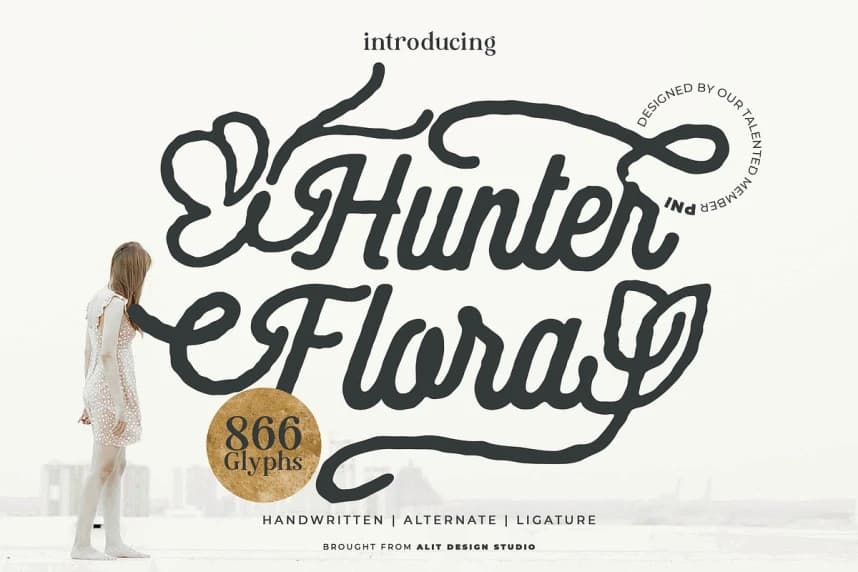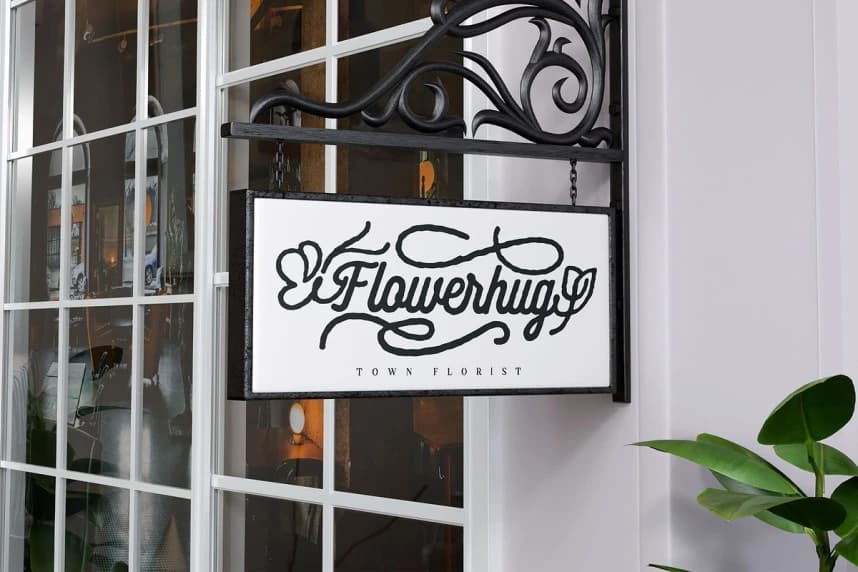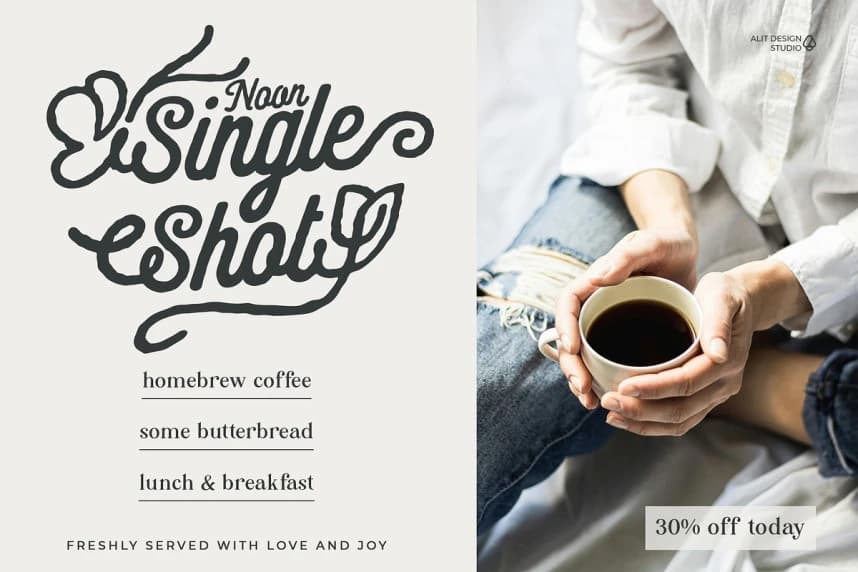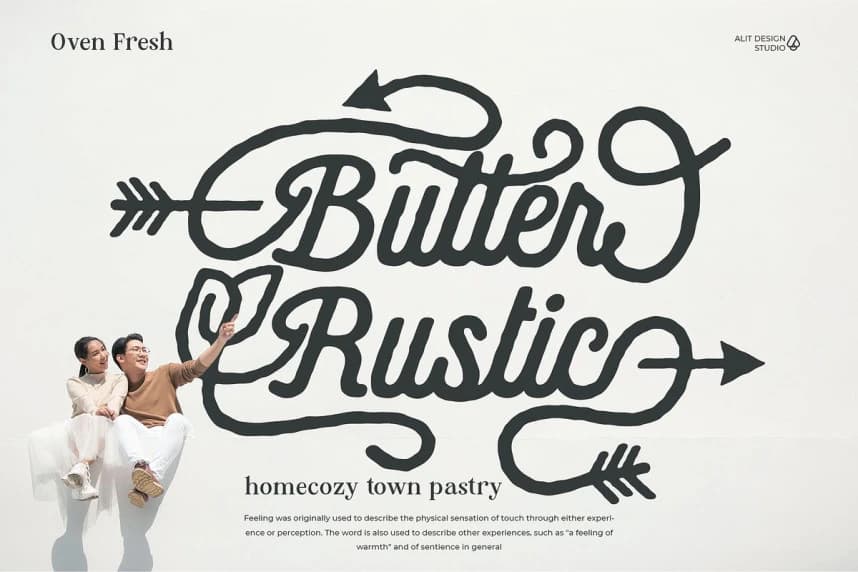
Hunter flora Font
Hunter Flora Font, Alit Design Studio tarafından sunulan özenle hazırlanmış güzel bir el yazısı fontudur. Projelerinize organik doğanın dokunuşunu ve neşeli bir çekiciliği katmak için tasarlanmıştır; Hunter Flora, gündelik zarafet ile yaratıcı çok yönlülük arasında mükemmel bir denge sunar.
Hunter Flora Font, Alit Design Studio tarafından sunulan özenle tasarlanmış bir el yazısı fontudur. Projelerinize organik bir doğa dokunuşu ve neşeli bir çekiclik katmak için tasarlanmıştır; Hunter Flora, gündelik zarafet ile yaratıcı çok yönlülük arasında mükemmel bir denge sağlar.